La nueva imagen de Walmart luego de 17 años: color, tipografía y más detalles de su nuevo logotipo en EE. UU.
Walmart renueva su identidad visual por primera vez desde 2008, incorporando un nuevo tono de azul oscuro denominado "True Blue" y una tipografía actualizada para conectar con las nuevas generaciones.
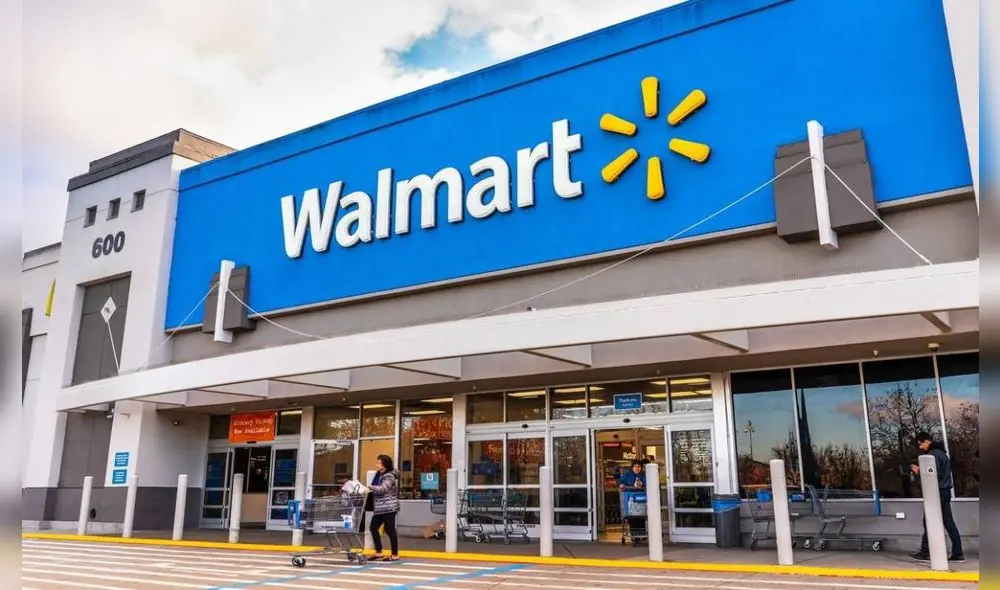
Walmart, famosa empresa del retail en Estados Unidos, ha decidido refrescar su identidad visual por primera vez desde 2008. Esta modificación incluye un nuevo tono de azul más oscuro, llamado "True Blue", una tipografía más gruesa y un diseño modernizado que honra las raíces de la gigante compañía, principalmente al fundador Sam Walton. En la siguiente nota te detallamos su nuevo color, tipografía y más detalles de su nuevo logotipo en EE. UU.
El rediseño no solo busca actualizar la estética de la marca, sino también adaptarse a un mercado en constante evolución. Con un crecimiento sólido en sus ventas y un notable incremento en el valor de sus acciones, Walmart se posiciona para conectar con las nuevas generaciones y reforzar su liderazgo en el sector minorista.
Desde enero de 2025, los cambios son visibles en su sitio web, aplicación móvil y campañas de marketing, mientras que algunos ajustes comenzaron a implementarse en octubre de 2024, coincidiendo con la apertura de su nueva sede corporativa en Bentonville.
¿Cuál es el nuevo color, tipografía y nuevo logotipo de Walmart en EE. UU.?
La marca ha adoptado un tono más sofisticado y contemporáneo que el anterior, denominado "True Blue". Este nuevo color no solo moderniza la imagen de Walmart, sino que también busca resonar con un público más joven y digitalmente conectado.
La nueva tipografía, inspirada en el estilo "Antique Olive" de las décadas de los 80 y 90, presenta un diseño actualizado que fusiona modernidad y nostalgia. Este detalle no solo es estético, sino que también evoca la historia de la marca y su fundador, Sam Walton.
El diseño modernizado permite que la chispa se separe ligeramente del nombre en ciertos espacios, como escaparates, y se ajuste mejor a múltiples aplicaciones, incluyendo bolsas, aplicaciones y campañas digitales. Esta flexibilidad es crucial en un entorno donde la innovación visual es clave para destacar.
Un enfoque colaborativo en el rediseño
El proyecto fue desarrollado por el equipo creativo interno de Walmart, en colaboración con agencias externas de renombre como JKR, Landor y Publicis. Este enfoque de trabajo en equipo ha sido fundamental para alcanzar un resultado que no solo es visualmente atractivo, sino que también refleja la esencia de la marca.
Más que un simple cambio estético, esta actualización refleja la intención de Walmart de mantenerse relevante en un mercado competitivo. Con el nuevo diseño, la marca busca conectar con las nuevas generaciones, reforzar su liderazgo y honrar su legado, integrando elementos que evocan la historia de Walmart y su fundador.